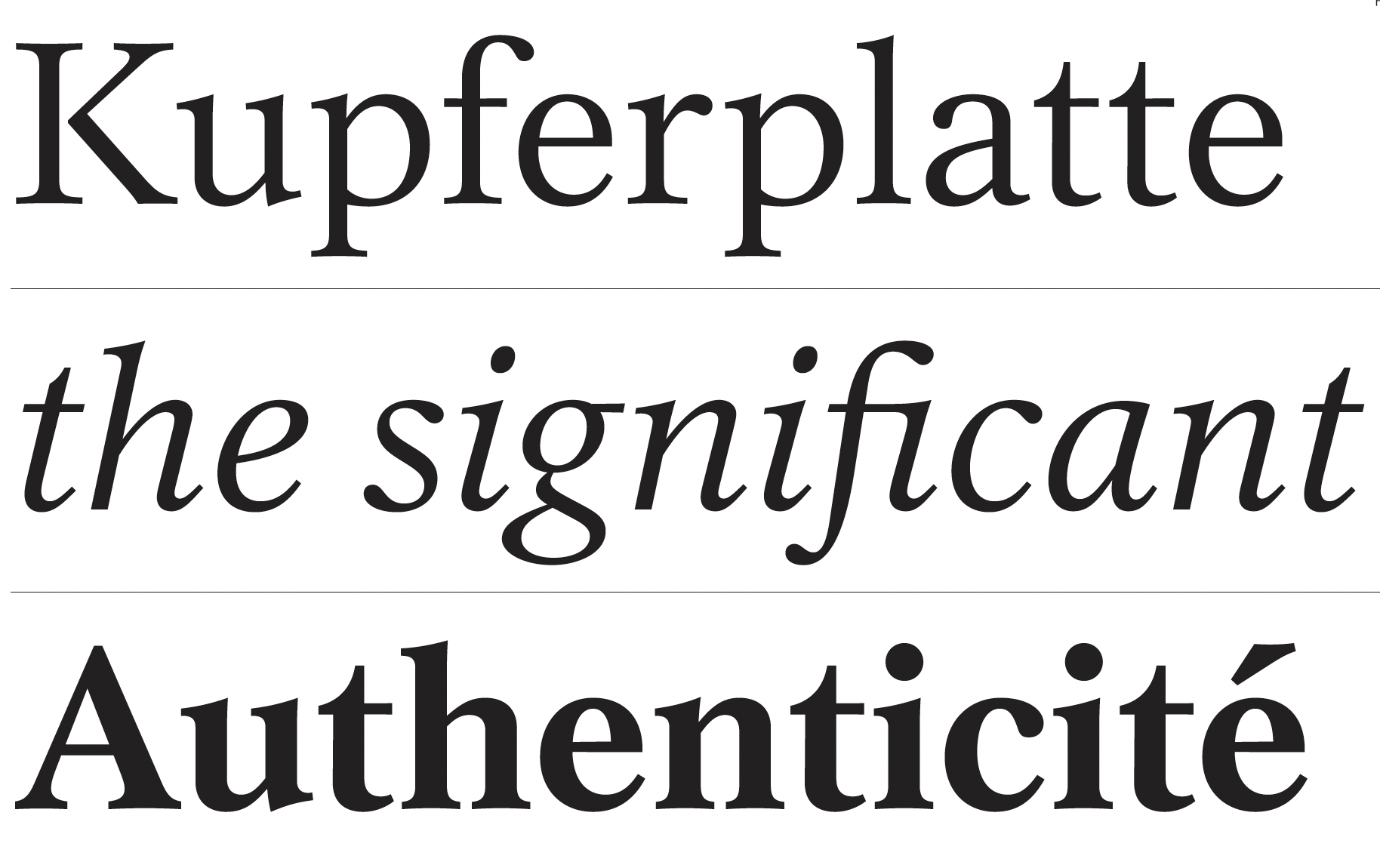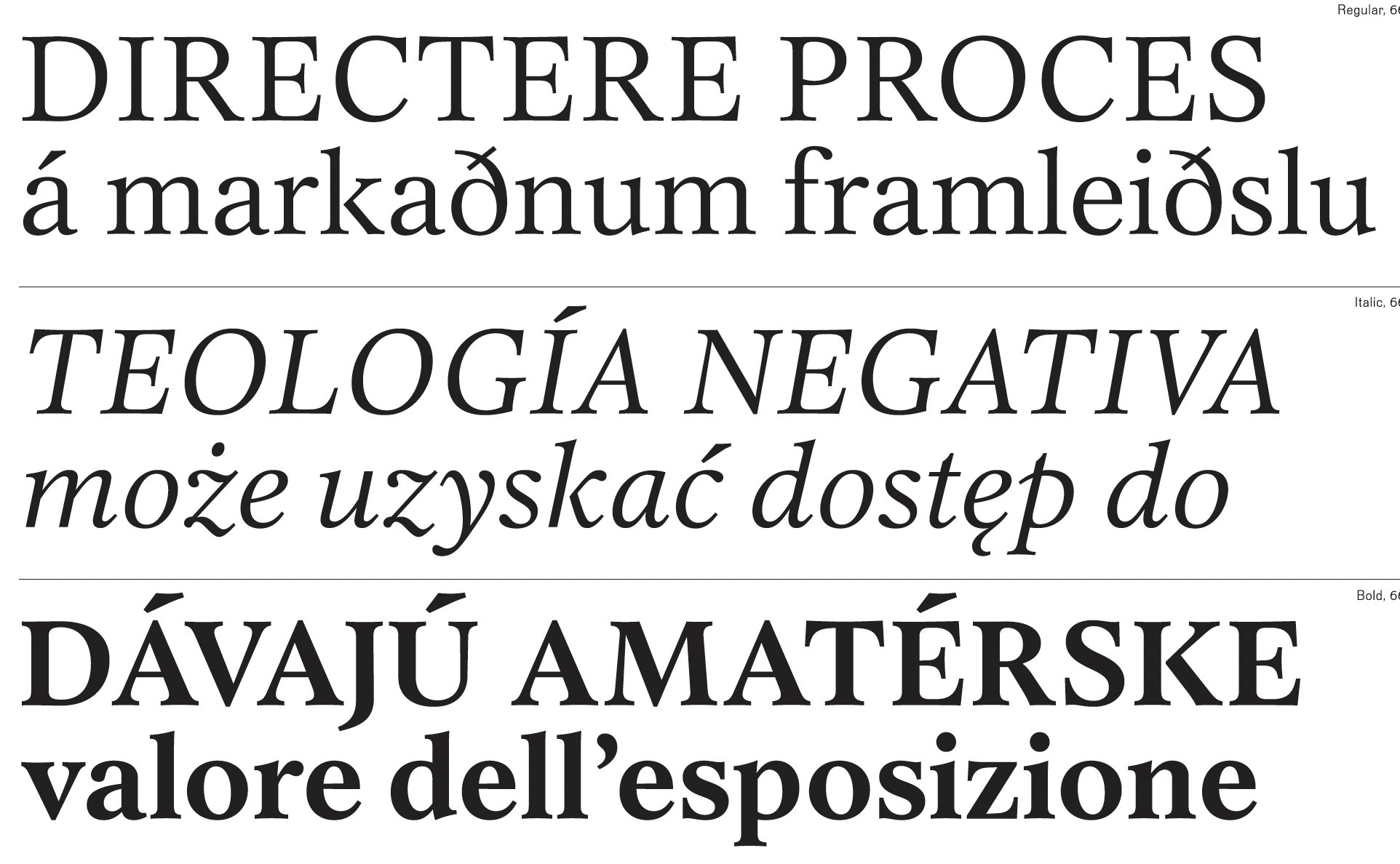
- Antiqua humanistisch
- Versaleszett:
- enthalten
In den 1960er-Jahren wurde Gert Wunderlich beauftragt, eine Schriftvorlage zu überarbeiten, die Lektor-Antiqua hieß und vermutlich von Herbert Thannhaeuser stammte. Die entstandenen Schnitte wurden jedoch nicht veröffentlicht und erst mit den neuen Möglichkeiten des Fotosatzes in den 1980er-Jahren erneut bearbeitet. Dieses Mal kam jedoch die Wende und das Ende von Typoart dazwischen. Zwischen 2015 und 2017 wurde das Design schließlich im dritten Anlauf von Reymund Schröder in Abstimmung mit Gert Wunderlich in drei Schnitten ausgebaut und über Forgotten Shapes veröffentlicht.